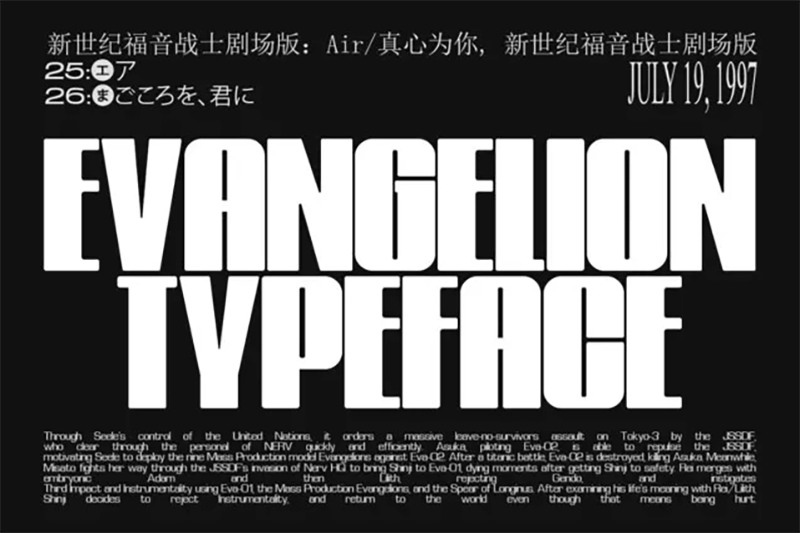
Tác giả: Domenico Barreto
Phân loại: Cá tính
Kiểu chữ: Serif
Font Evangelion là mẫu font chữ design nổi bật với các nét đậm cô đọng, được sử dụng trong loạt anime nổi tiếng “Neon Genesis Evangelion”. Mẫu Font này được biết đến với phong cách hiện đại, có phần góc cạnh và mang đậm chất tương lai, gắn liền với thương hiệu và thiết kế của series. Font Evangelion là lựa chọn phù hợp để tạo nên các dòng tiêu đề in đậm và làm nổi bật các loại ấn phẩm thiết kế, thu hút sự chú ý của người xem.